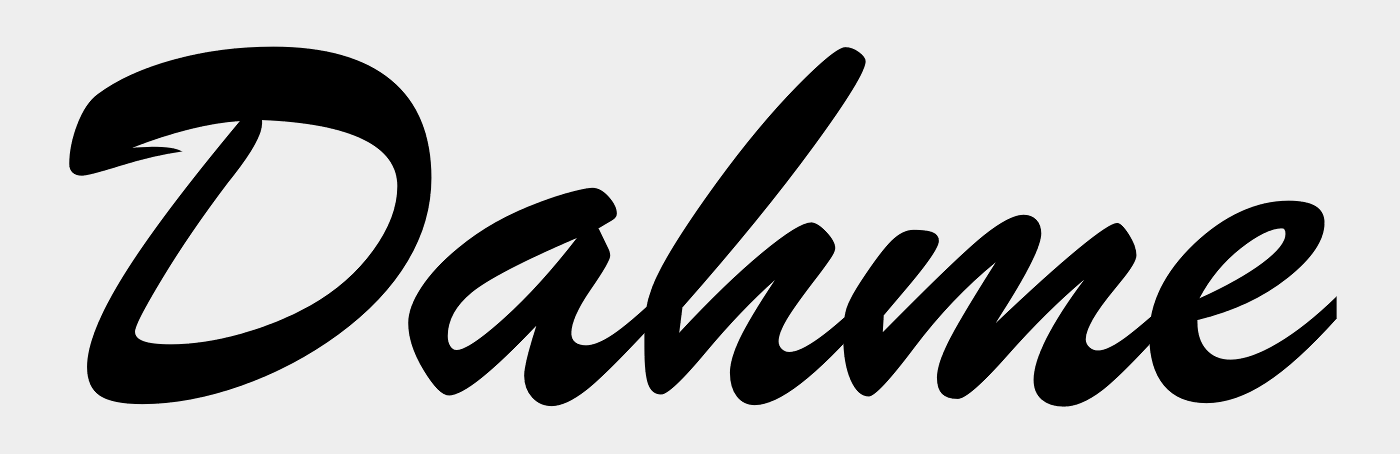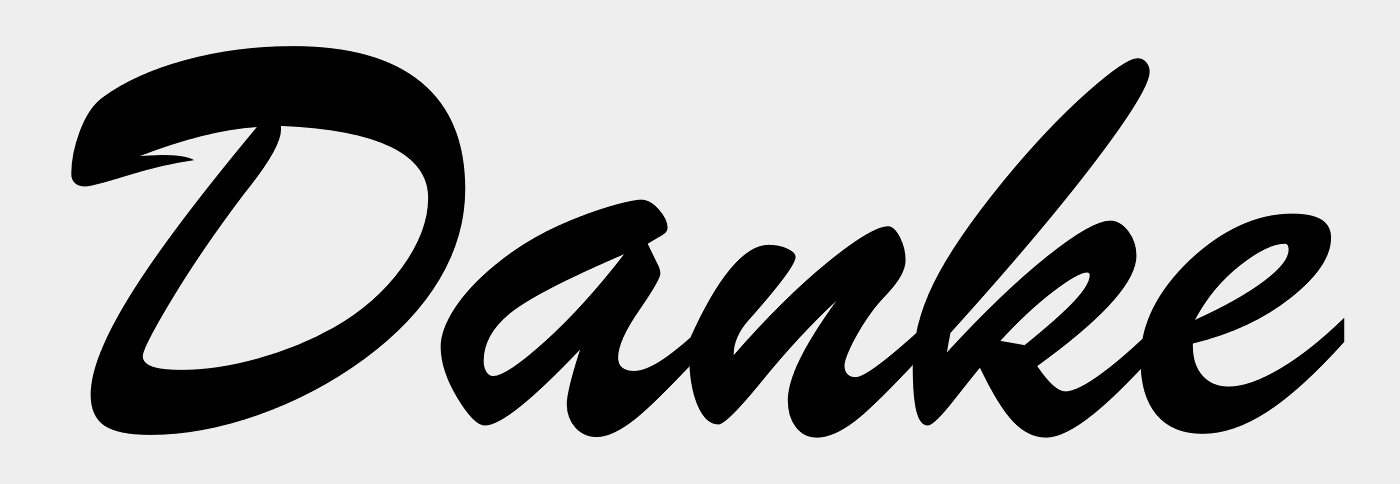
Hallo suche die Schriftart zum folieren eines fahrschulautos.
Es handelt sich um diese Schrift: R.Dahme auf dem Logo sowohl wie auf dem X1 auf der Internetseite.
Brush Script
(ist übrigens im CorelDraw-Paket von Anfang an drin, und dürfte wohl auch hieraus verwendet wurden sein, da viele Folienschnippler mit Corel arbeiten)
Und bitte die Brush nicht sperren wie auf der Netzseite. Das ist eine Pinselschrift, da müssen die Buchstaben verbunden sein.